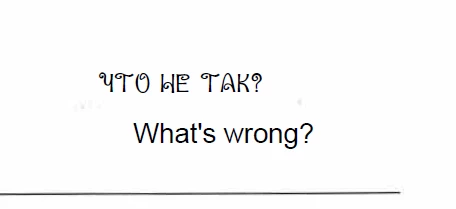
Как изменить русский шрифт с клоунского на нормальный?
Я следовал инструкции и выбрал шрифт Calibri, при этом к английскому шрифту эти настройки были применены, а русские буквы веселые как в мультике. Если бы я был клоуном и писал письмо Деду Морозу, возможно меня это устроило бы. Но мне нужно отредактировать деловой документ. Как решить эту проблему?